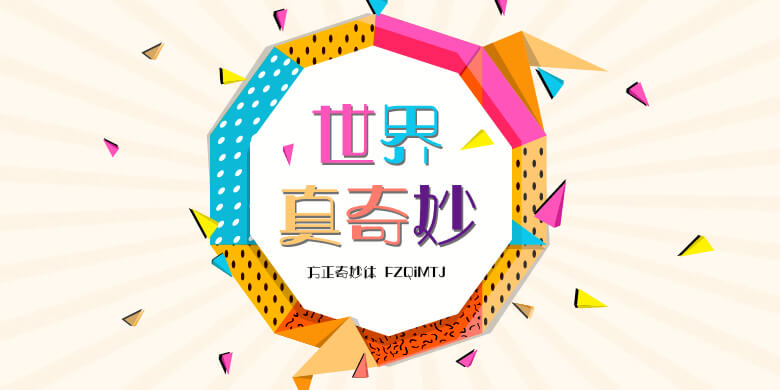
方正奇妙体-简繁-ExtraLight
奇妙体:创意灵感来自一家外国时装店大减价的宣传,看见它广告中的外文字体好有个性,所有重心都向下移的,而中间留下一段大空间,好特别,好有特色,所以郭老师便利用这罕有的布局,大胆设计了“奇妙体”,整体完成后,把它做横,直排列测试,发现风格独特,时尚高雅,品味出众,笔划都以横细直粗,增强了美感,充满个性的字体太诱惑了。是中国第一款匠心独运的佳作!它共有8种粗细,商业用途广泛,男女老少都合适,如手机字体,动画,化妆品,女士饰物、时装、酒店、饮料广告宣传和包装设计等!